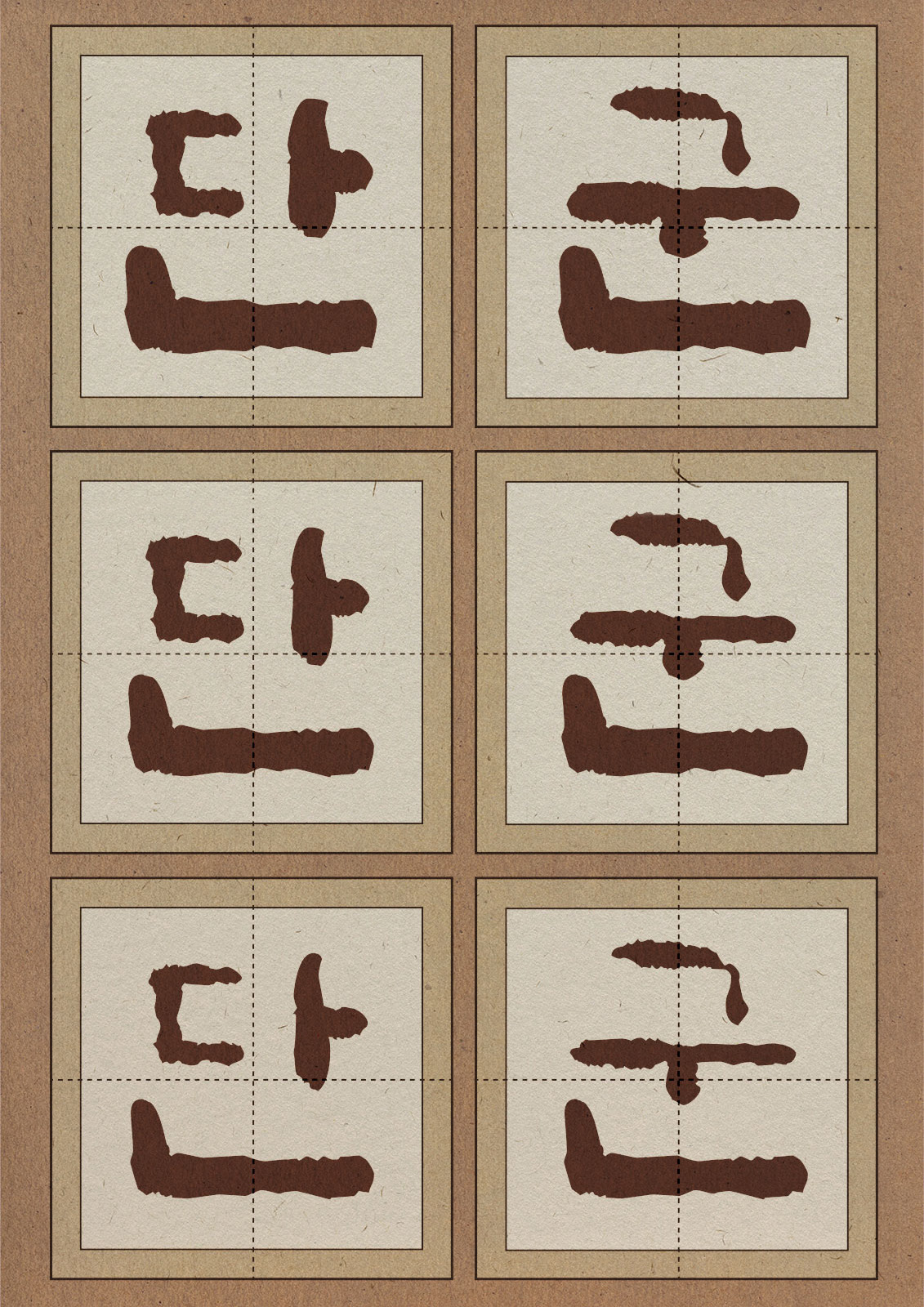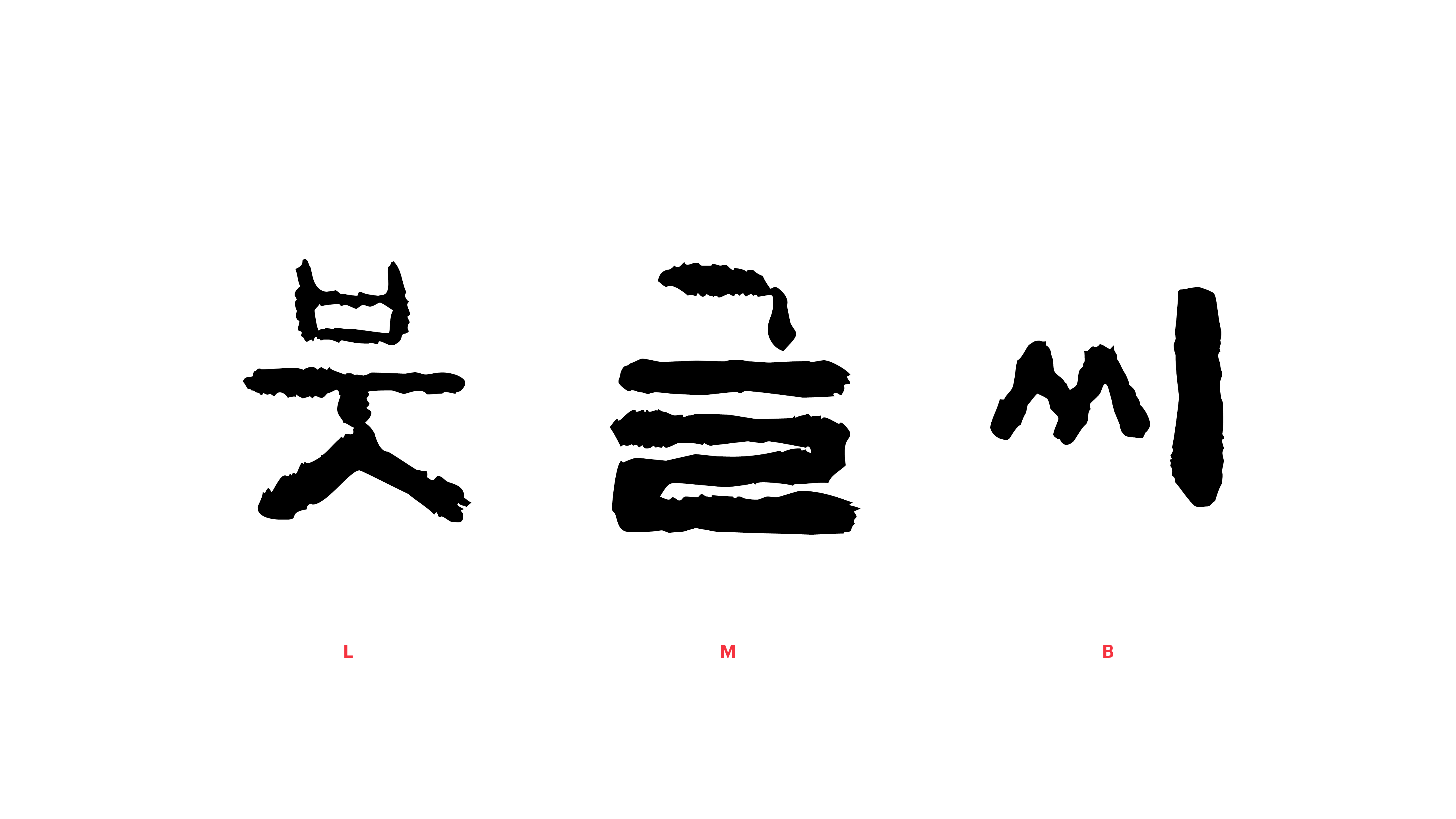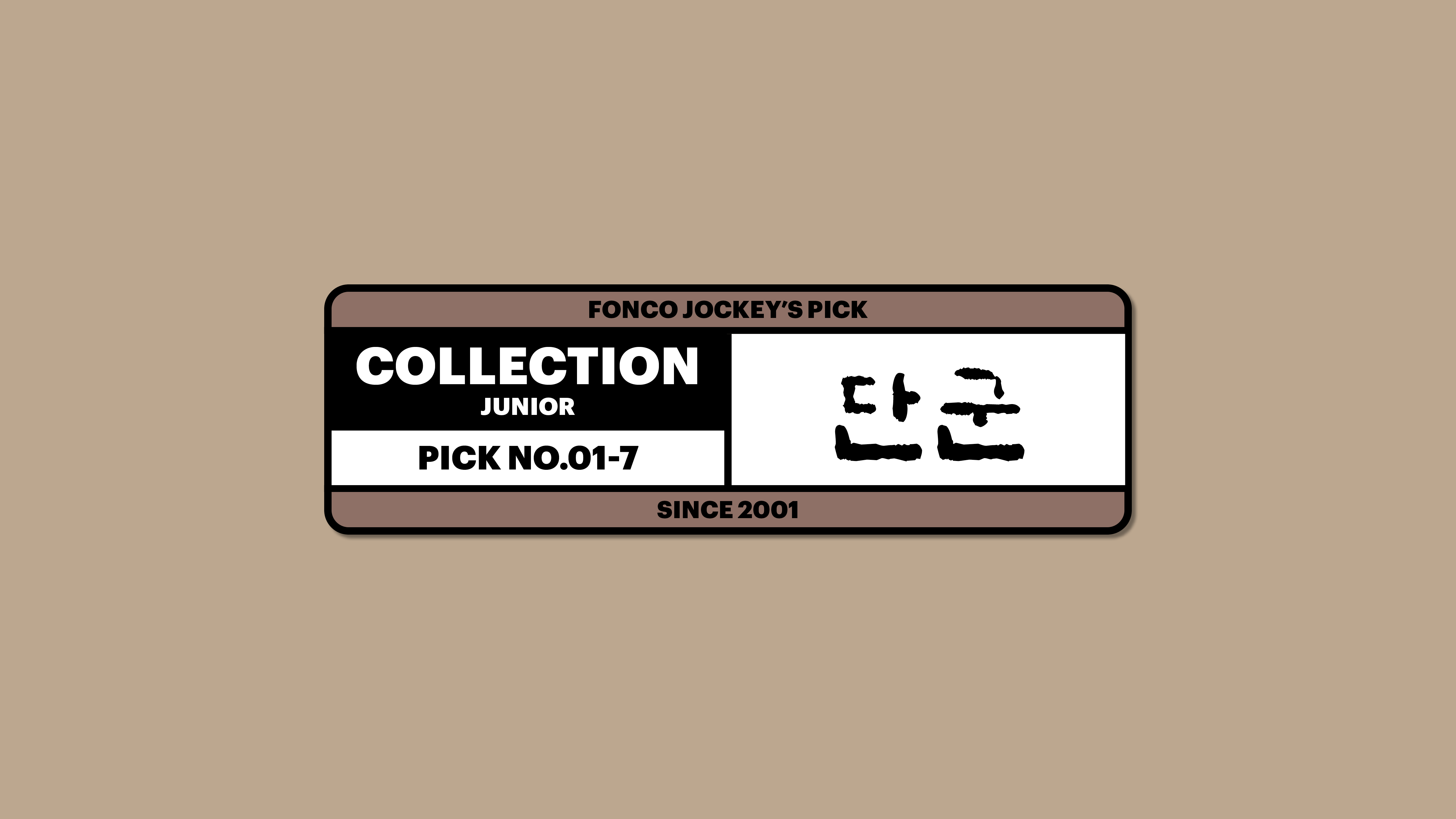
단군
Yoon 단군
마치 구름의 흐름을 보듯, 웅장하면서도 몽환적인 감성이 느껴지는 붓글씨 폰트입니다. 종성의 크기가 초성, 중성에 비해 크게 강조되어 있어 조형적 안정감이 느껴지지요. 그뿐인가요? 붓글씨 특유의 감성과 먹의 질감이 적절하게 살아 있어 우리의 감수성을 콕, 콕 자극합니다.